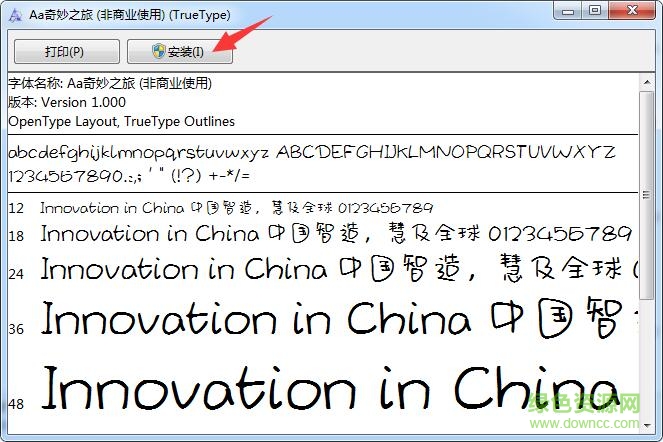
aa奇妙之旅ttf字體是一個免費的aa字體文件。此字體可以用來設(shè)計海報、廣告等,支持中英文輸出。書寫的文字比較偏卡通風(fēng)格。喜歡的用戶歡迎在綠色資源網(wǎng)下載使用。
Aa奇妙之旅(非商業(yè)使用)字體家族系列主要提供常規(guī)等字體風(fēng)格樣式。適合應(yīng)用與藝術(shù)設(shè)計、平面宣傳設(shè)計、網(wǎng)頁設(shè)計,書法字帖等領(lǐng)域!